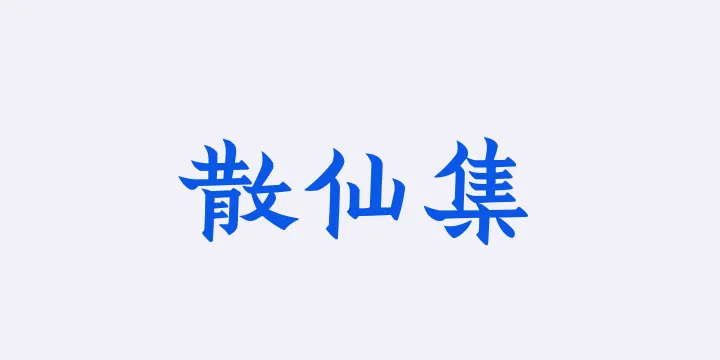
Aa散仙集 By Aa字库 商用字体
字体全名: Aa散仙集
铸字厂: Aa字库
设计师: Aa字库
字体简介: 本字体吸收原字形“弃圆转、弃流畅、重方折、重金石”的特点,并加以几何化处理,在横收笔和横折等处设计了宋体折角,长横重而有力,起笔粗重翘头而行笔渐收,点画如斜风吹雨,溅落为长水滴形,与微倾的横画一起拖动整体字势沉向右下。横竖起笔有锐利、横向切入的起笔,矢量化后的曲线更加柔和雅致,进而拥有更广泛的应用场景。整字结构上为左侧横起笔和拖长的撇余留更多空间,左舒展右紧凑,结合笔画分布形成错落不规则的字形轮廓。